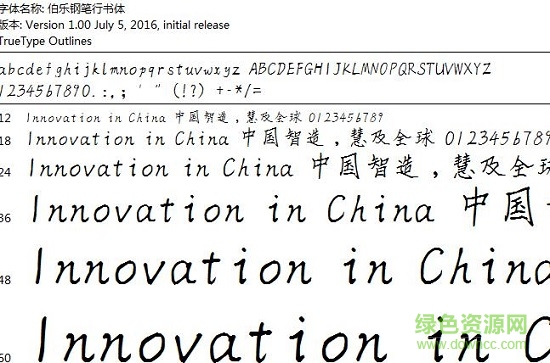
伯樂鋼筆行書字體
伯樂鋼筆行書是一款專為喜歡書法自字體的朋友準(zhǔn)備的鋼筆字體,這款字體整體上看上去會(huì)覺得非常的賞心悅目,感興趣的朋友歡迎下載使用!
伯樂鋼筆行書體簡介
伯樂鋼筆行書體是一款根據(jù)鋼筆行書書法打造而來的書法字體,具有硬筆書法完美的特質(zhì),筆畫剛硬有勁,字跡如行云流水一般順暢,非常的具有欣賞價(jià)值!
伯樂鋼筆行書體